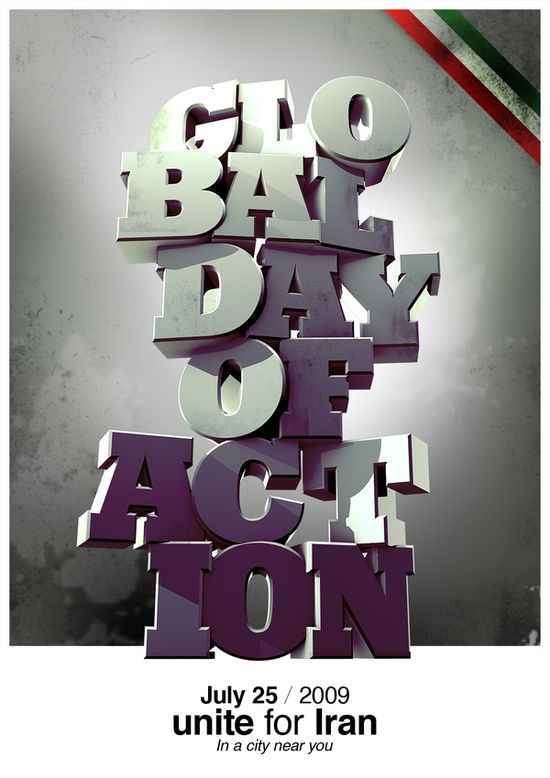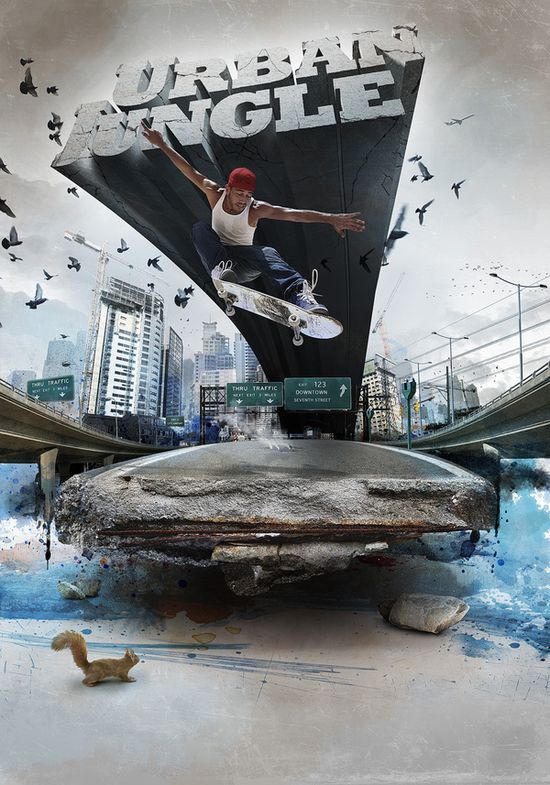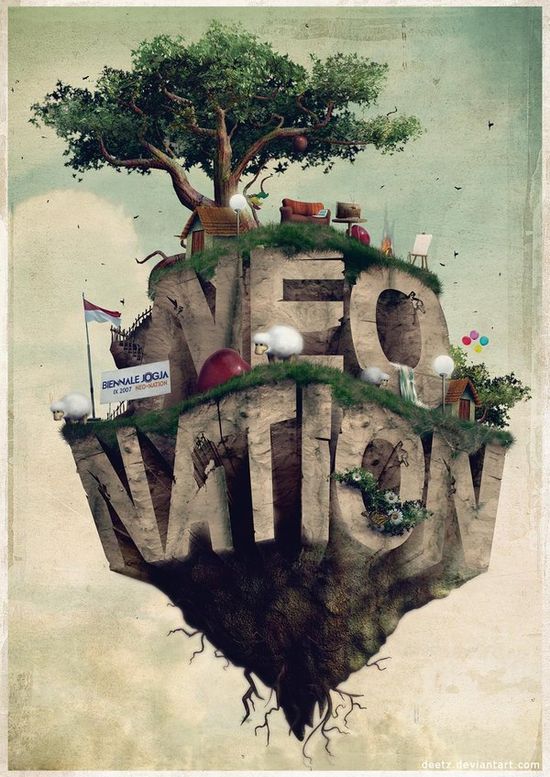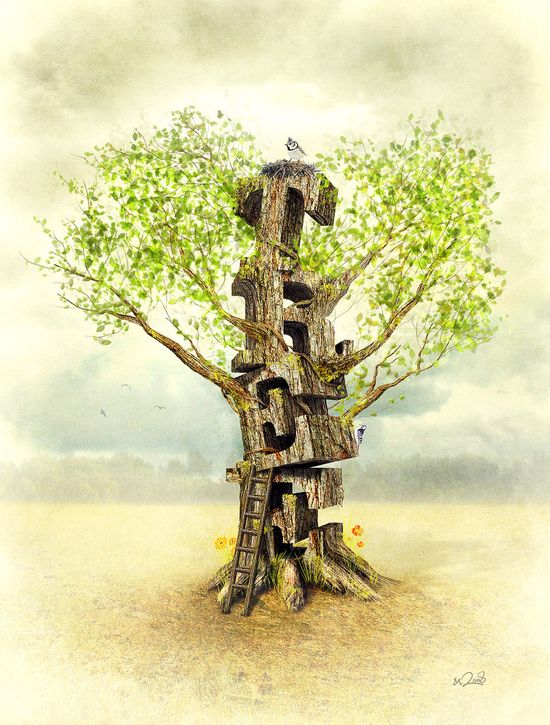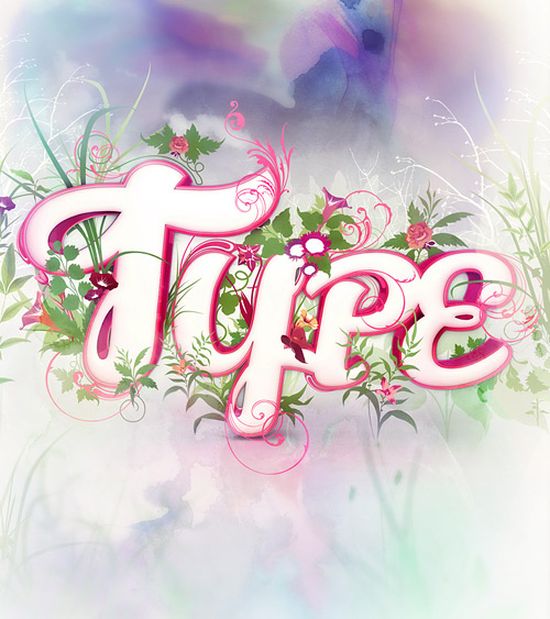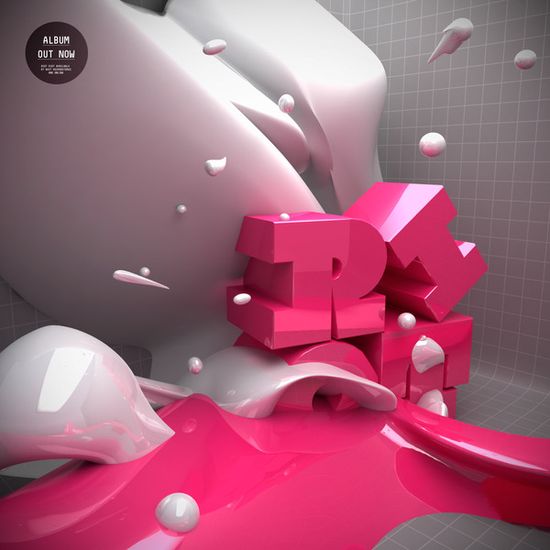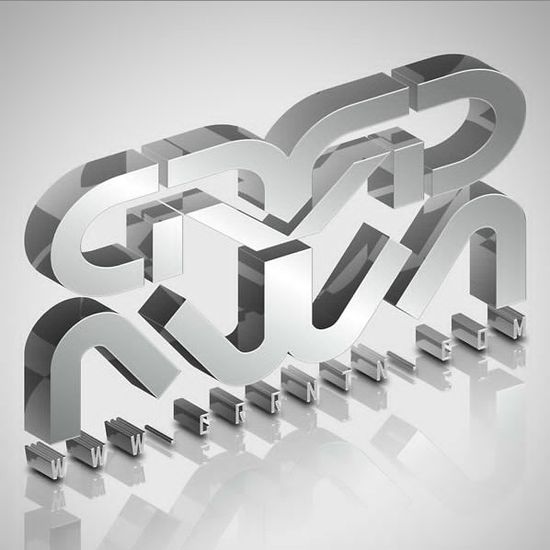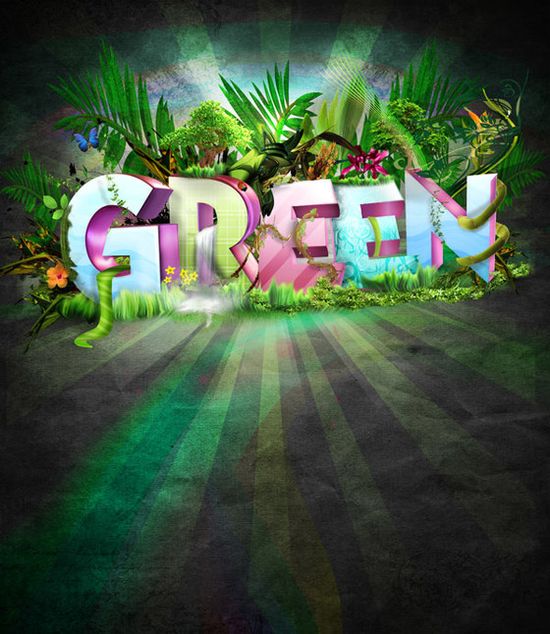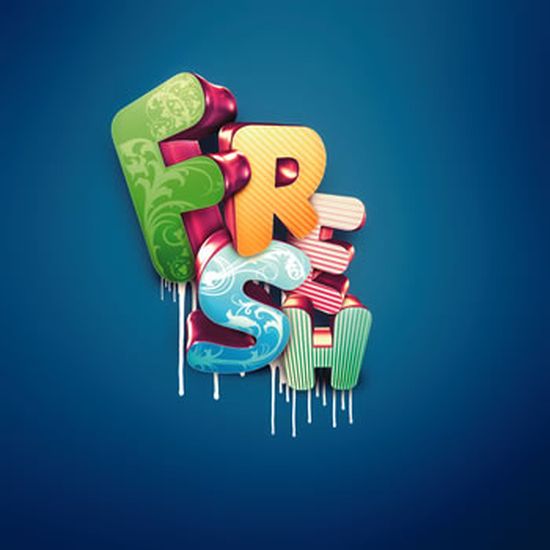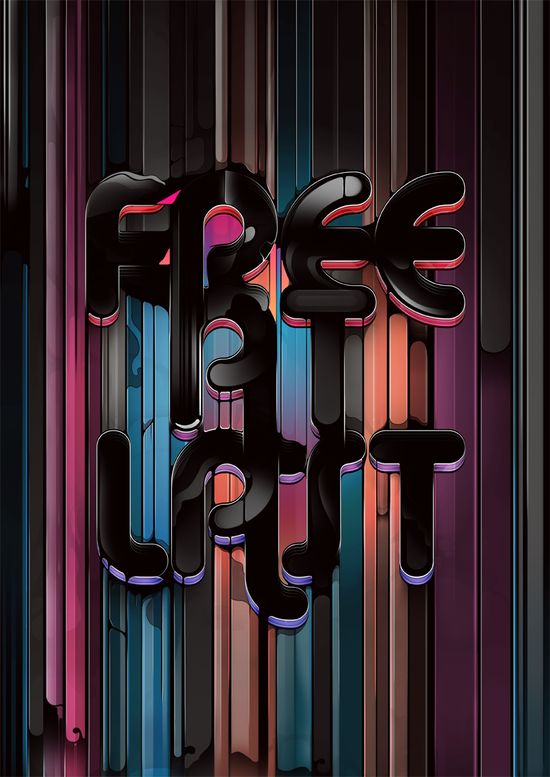
50 Exemplos de Tipografia 3D
A Tipografia muitas vezes consiste em ser 100% o destaque da arte. Seja no Photoshop, Illustrator ou programas em 3d, integrar a tipografia com fundos e com a arte sempre finaliza em ótimos resultados.
Abaixo 50 exemplos de tipografia 3d para você se inspirar em suas artes.